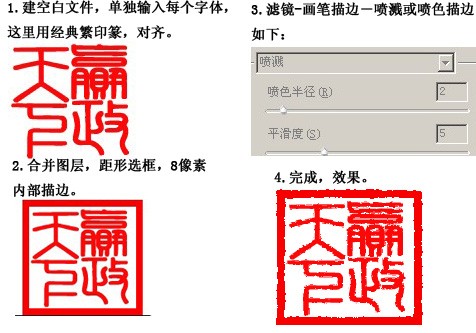
篆體,漢字古代書體之一,也叫篆書。是對古文字的統(tǒng)稱。“篆者,傳也,傳其物理,施之無窮?!惫湃苏J(rèn)為篆書為倉頡所造,其實(shí)是不可信的。一種文字的產(chǎn)生是要經(jīng)過一個(gè)較長的醞釀發(fā)展過程的,不可能有一個(gè)人在短時(shí)期能完成。
篆體即為篆書字體,篆體分為大篆和小篆體、是古代漢字書體之一,是秦國的通用文字,大篆的簡化字體,其特點(diǎn)是形體勻逼齊整、字體較籀文容易書寫。在漢文字發(fā)展史上,它是大篆由隸、楷之間的過渡。